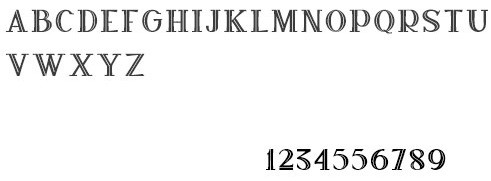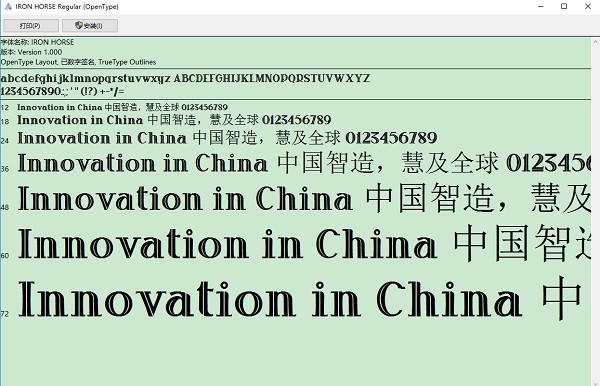
ironhorse英文字體非常的優(yōu)雅大方,整個(gè)字體非常的剛勁有力,上下左右的邊緣還略帶了輪廓陰影,有醒目的鏤空雙邊效果,非常的具有設(shè)計(jì)感,歡迎喜愛此字體的朋友下載體驗(yàn)!
字體設(shè)計(jì)優(yōu)美、秀麗大方,書寫流暢,整體效果非常漂亮
適合應(yīng)用于海報(bào)設(shè)計(jì)、書籍裝幀、畫冊(cè)封面、產(chǎn)品包裝設(shè)計(jì)等應(yīng)用